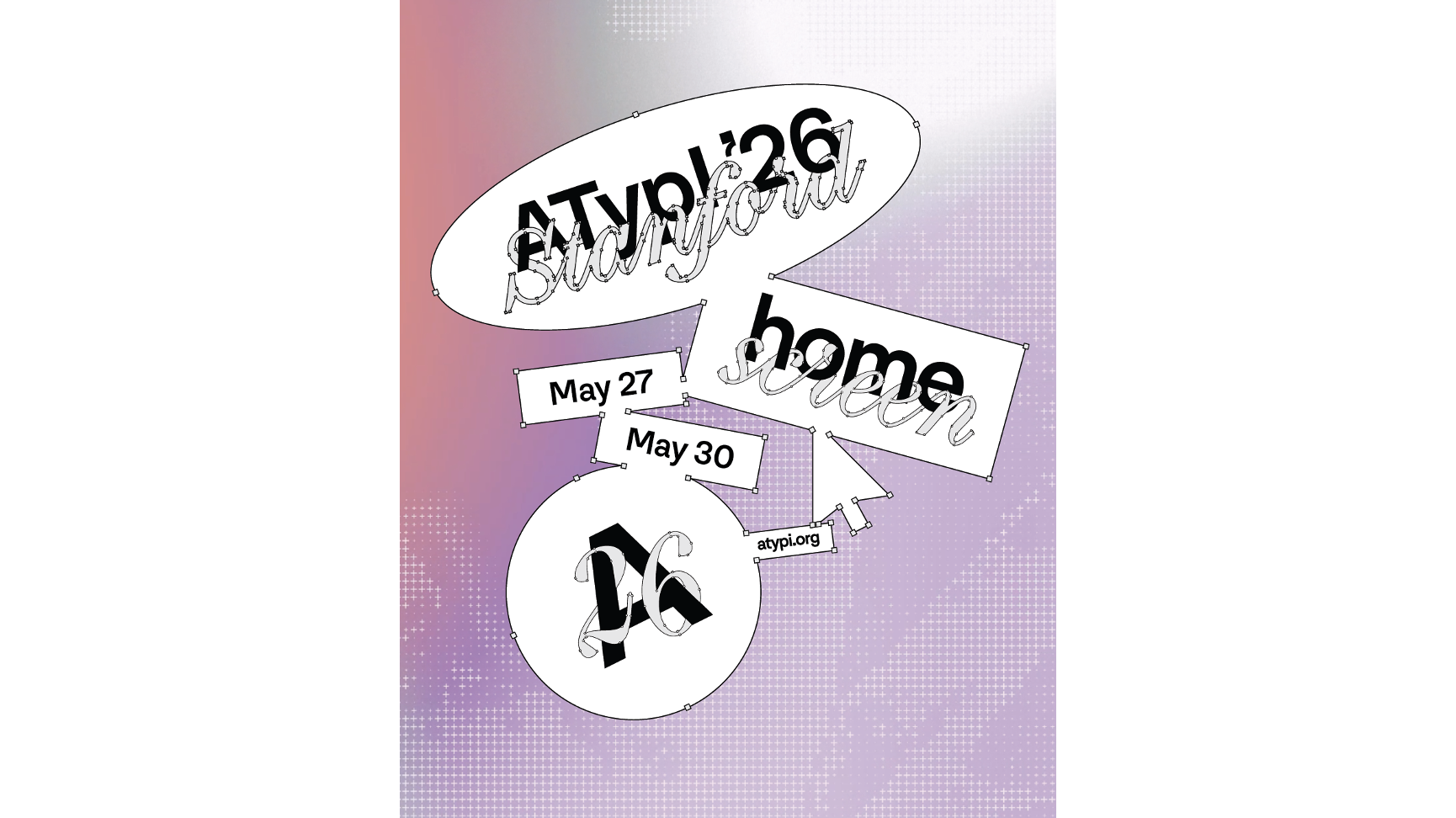
APACチームより土井遼太とChorong Kimが登壇、MonotypeはGold Sponsorとして協賛
米国 Monotype® Imaging Inc.の日本法人Monotype株式会社(東京都港区、以下 Monotype)は、2026年5月に米国・スタンフォード大学で開催される国際タイポグラフィカンファレンス「ATypI 2026 Stanford」において、クリエイティブ・タイプディレクター土井遼太とChorong Kimが登壇することをお知らせします。
Monotypeは本イベントのGold Sponsorとして協賛しています。
ATypIは、世界中のタイプデザイナー、研究者、教育機関、テクノロジー企業が集う、タイポグラフィとタイプデザイン分野における国際的なカンファレンスです。2026年は米国・スタンフォード大学にて開催され、グローバルなタイプコミュニティにおける最新の研究やデザイン、テクノロジーに関する議論が行われます。
プレゼンテーションについて
今回のセッションでは、韓国語、日本語、ラテン文字のサンセリフ体における「ゴシック」デザインの関係性に着目し、異なる文字体系間での視覚的な調和や書体設計について考察します。
CCJKおよびラテン書体を横断したタイプデザインの知見を共有し、多言語環境におけるフォントデザインの可能性を探ります。
ATypI 2025 Copenhagen アーカイブ動画公開について
また、2025年にデンマーク・コペンハーゲンで開催された「ATypI 2025 Copenhagen」のアーカイブ動画も公開されています。
CCJKグリフデザインの強化:グローバルデザイナーのエンパワーメント
Monotype APACチームによる過去セッションでは、CCJKデザインや多言語書体設計に関する知見を共有し、国際的なタイプコミュニティに向けて発信を行いました。
ATypIでは、過去の講演や研究内容を継続的に公開しており、タイポグラフィやタイプデザインに関する学びと交流の場としても広く活用されています。
ATypIとは
ATypI(Association Typographique Internationale)は、1957年に設立された、タイポグラフィと書体デザインを専門とする国際的な非営利団体です。毎年開催されるカンファレンスでは、世界各国のタイプデザイナーや研究者による講演、ディスカッション、ワークショップなどが行われています。
【登壇者プロフィール】
土井遼太
Monotype クリエイティブ・タイプディレクター
東京藝術大学デザイン科卒業後、英国レディング大学書体デザインコースにて修士号を取得。2015年よりMonotypeに在籍し、企業制定書体の開発や書体コンサルティングに従事。たづがね角ゴシックをはじめ、多言語書体開発やCCJK対応プロジェクトに携わる。近年は大学での講義や国際カンファレンスへの登壇など、国内外でタイポグラフィに関する発信を行っている。
【主な関連書体】
・Shorai® Sans
・たづがね® 角ゴシック
Chorong Kim
Monotype クリエイティブ・タイプディレクター
韓国語およびラテン書体を専門とするタイプデザイナー。Monotype APACチームに所属し、多言語環境における書体設計やグローバルブランド向けタイプデザインに携わる。韓国語とラテン文字の調和を重視した書体開発を通じて、国際的なタイプデザイン領域で活動している。